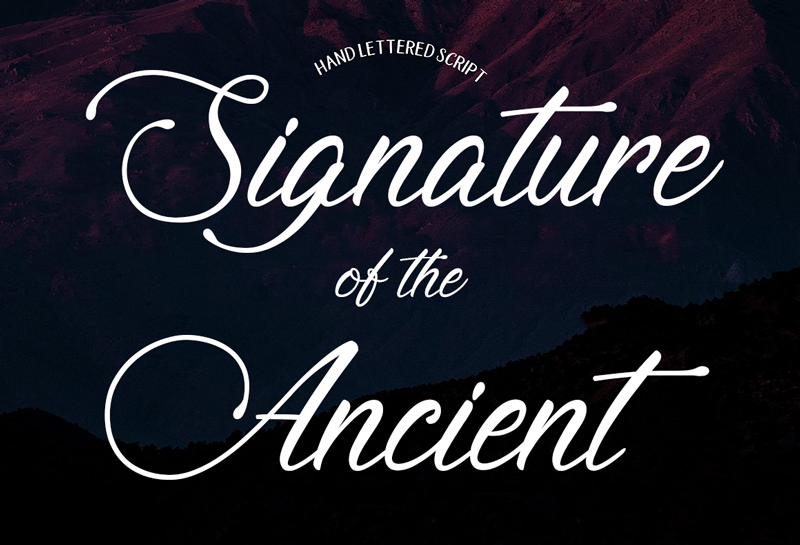
Signature of the Ancient Font – Fonte Grátis
Signature of the Ancient Font
Introduzimos a Signature of the Ancient Font! Esta fonte moderna com estilo script está adaptada para múltiplos projetos, desde cartas e convites de casamento até editoriais e campanhas de moda. Seu design fluido e elegante é perfeito para criar mensagens fortes em sua identidade visual ou artesanato personalizado. Ideal tanto para se tornar o destaque em seu próximo poster ou impressão de blog, quanto para dar um toque único a suas cartas e convites, a Signature of the Ancient Font oferece uma versatilidade que irá cativar qualquer designer. Este é um recurso gráfico valioso para quem procura adicionar um toque distintivo aos seus materiais, seja em design editorial, marca ou no seu trabalho de artesanato.